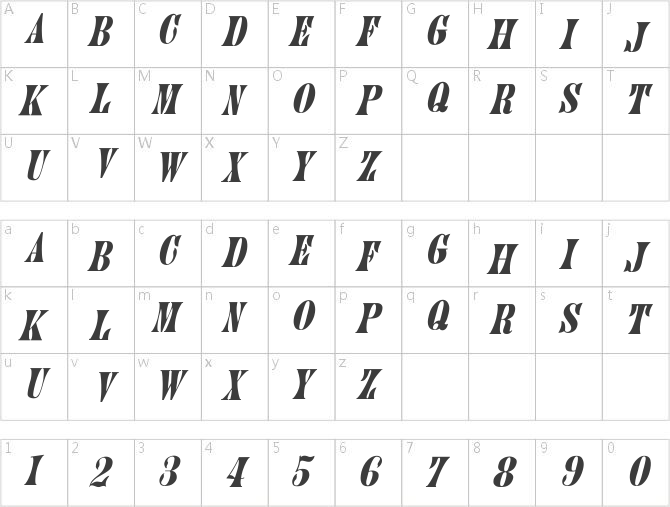
Juniper-Normal-Italic 詳情頁
Juniper-Normal-Italic字體字庫是一款讓人賞心悅目、百看不厭的英文字體,適合各類廣告和產(chǎn)品包裝設(shè)計(jì)應(yīng)用,字體大小0.1MB,格式為ttf字體,上傳用戶是洛洛,作者/版權(quán)方為未知